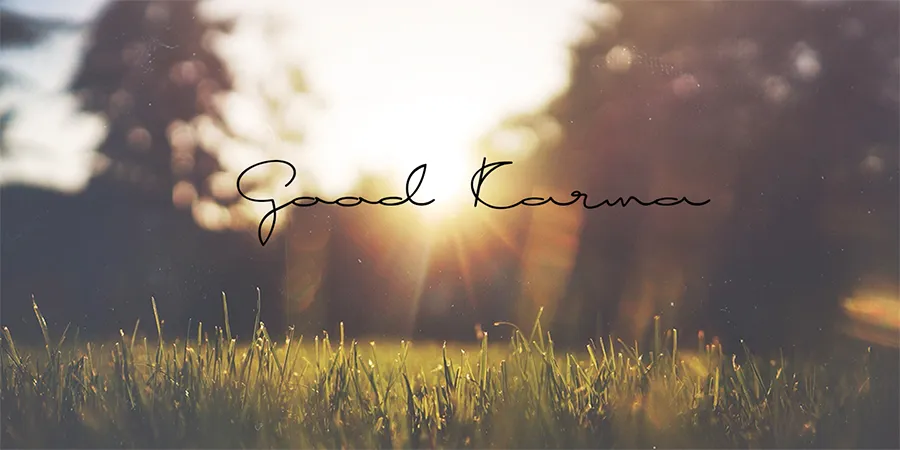
A ‘Good Karma’ é uma fonte para escrita a mão cívilizada com estilo que combina características simples e linha monolítica com caracteres espontâneos e ondulantes, tornando-a perfeita para uso em qualquer tipo de projeto visual, desde cartas de casamento até a criação de design de cartões de felicitações. Esta fonte é uma ótima escolha para aqueles que buscam um toque natural e elegante para seus projetos, garantindo um resultado profissional e sofisticado em qualquer aplicação. Ela foi criada pelo designer Hamilton, oferecendo designers e criadores de conteúdo a opção perfeita para adicionar personalidade e charme ao seu design.